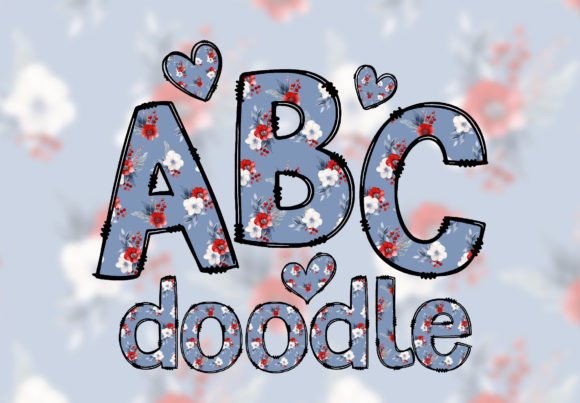
Floral Bulletin Board Letters Font PNG
浪漫花朵字母板字体PNG
** **完美的设计工具:手绘字母与绘画元素
**浪漫花朵字母板字体PNG是一款独特的字体套装,包含手绘字母与绘画元素,添加一种不可思议的魅力给您的作品!
这款字体套装完美适用于邀请函、贺卡、海报等设计项目,透明的PNG文件背景使得您可以轻松将它们整合到您的设计软件中。每个字母都有一个独特的故事,等待您去发现。无论您是设计师还是爱好者,都可以使用我们的浪漫花朵字母板字体PNG,让您的设计脱颖而出。
产品特点
- **完整的字母表**:包含所有大小写字母、数字和特殊符号(包含2个❤️心符号)
为什么选择浪漫花朵字母板字体PNG?
浪漫花朵字母板字体PNG是您的设计梦想的实现!它提供了一个无限的创意空间,让您可以自由地设计和定制您的作品。无论您是设计师还是爱好者,都可以使用我们的字体套装,创造出独特且个人化的作品。不要犹豫,立即下载浪漫花朵字母板字体PNG,开启您的创造之旅!